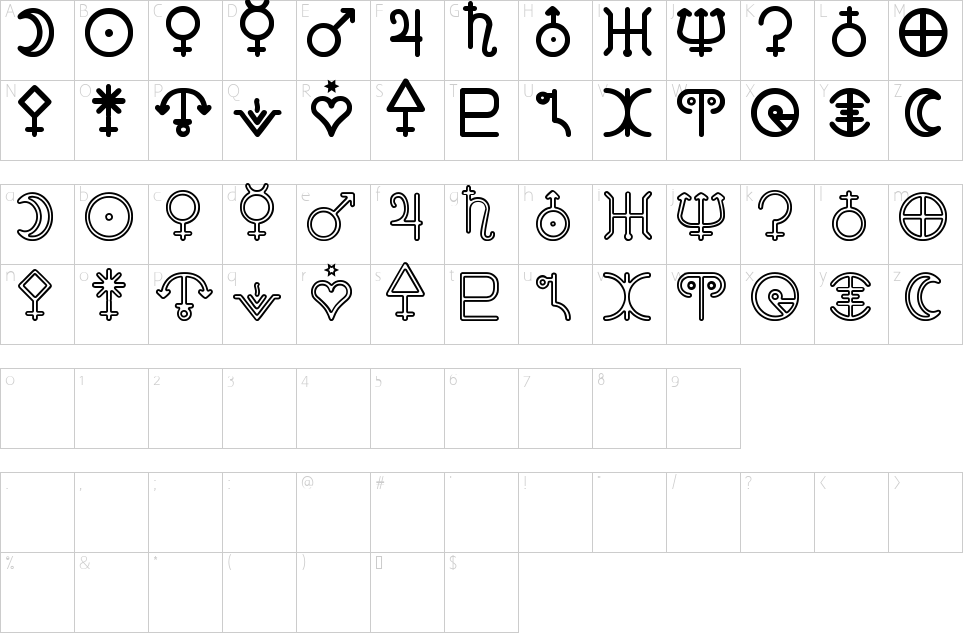
Astronomic Signs St é uma fonte estilosa e única, criada pelo designer Southype, disponível tanto para Windows quanto para Mac. Esta fonte é perfeitamente adaptada para criar gráficos visuais atraentes, especialmente para temas relacionados à astronomia. Se você é fã de estilos futuristas ou gosta de criar gráficos com uma leve dose de misterio, Astronomic Signs St é uma escolha perfeita. Com seu design atraente e semelhante a uma fonte sci-fi, esta fonte pode ser usada para criar cartazes, títulos de filmes, ou até mesmo artigos científicos sobre astronomia. Com 5.416 downloads, é claramente uma opção popular para quem busca personalidade e elegância em suas fontes. Se você está procurando por algo novo e criativo para adicionar ao seu arsenal de fontes, Astronomic Signs St é certamente uma opção a considerar.